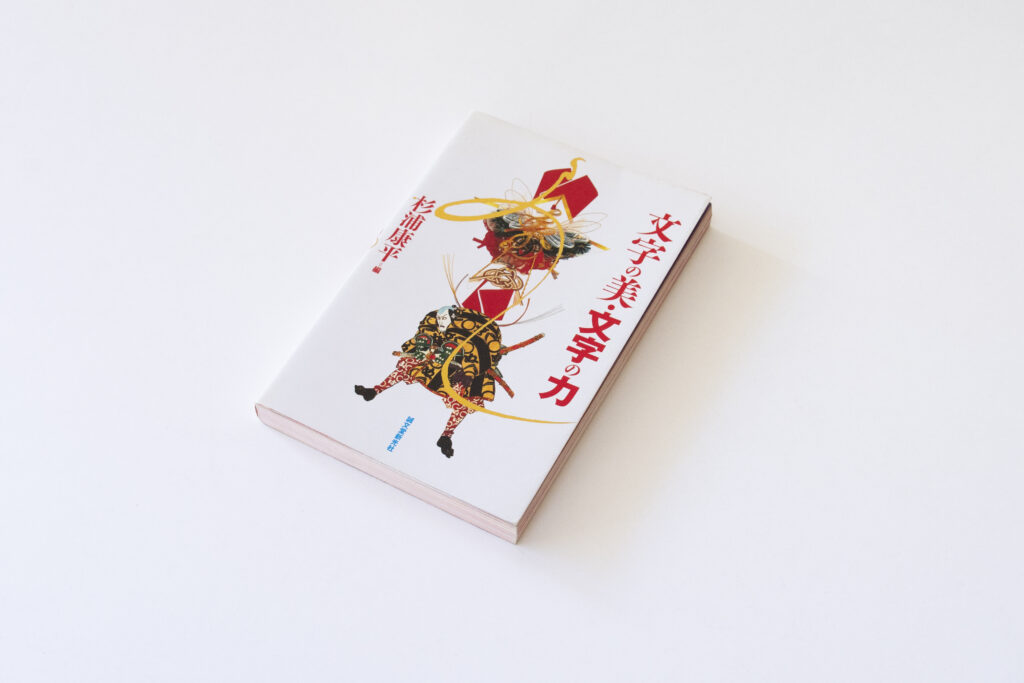
TPの書庫から『文字の美・文字の力』
今回は、杉浦康平編の「文字の美・文字の力」を紹介します。
この本にはアジア圏の様々な文字意匠がまとめられています。韓国の文字絵、京都の「大」文字焼きや、「壽」を印した中国の隈取り、クメールの男性の肌に広がる文字護符の文身など。筆者のアジア文字研究の資料の中から選ばれて掲載された文字意匠は、80点に及びます。
本書は、それらの文字意匠を特徴ごとに分けた5つの章で構成されています。「文字液が流れる文字」「文字を纏う」「文字を戴く(かぶる)」「文字を運ぶ」「文字と暮らす」の5つで、「文字を纏う」では民族衣装と文字。「文字を戴く」では宝冠と文字……といった具合に、章に関連する装飾品と文字が並び、作り手が装飾品に込めた想いを文字から垣間見ることができます。
著者のコメントに「いずれもが意表をつく場所に現れ、想像を超える姿態をもつ文字達です。」とある通り、現代ではあまり見ない文字の扱われ方とフォルムが載っています。先人達は文字に想いを乗せ、身近に扱い、文字の形そのものにも魅力を見出していたように感じます。「単なる記号に止まらない、記号性をはみ出した文字の活力」がそこにはあります。
全ての文字意匠に解説もついているので、字の形が好きな方や、人と文字の文化に興味がある方にオススメできる一冊です。先人達と文字の関わり方を知ることができます。
以下、タイププロジェクトの代表・鈴木功から『文字の美・文字の力』へのコメントと関連書籍の紹介です。
文字は身近にあって間口が広いため、興味をもちはじめるとキリがない。それに加え、奥が深くて鬱蒼としていて、いちど迷い込んだら出られなくなる。というのは大袈裟だが、文化の底力が文字に宿ることを『文字の美・文字の力』は教えてくれる。
『文字の美・文字の力』
構成・編:杉浦康平
発行:株式会社 誠文堂新光社